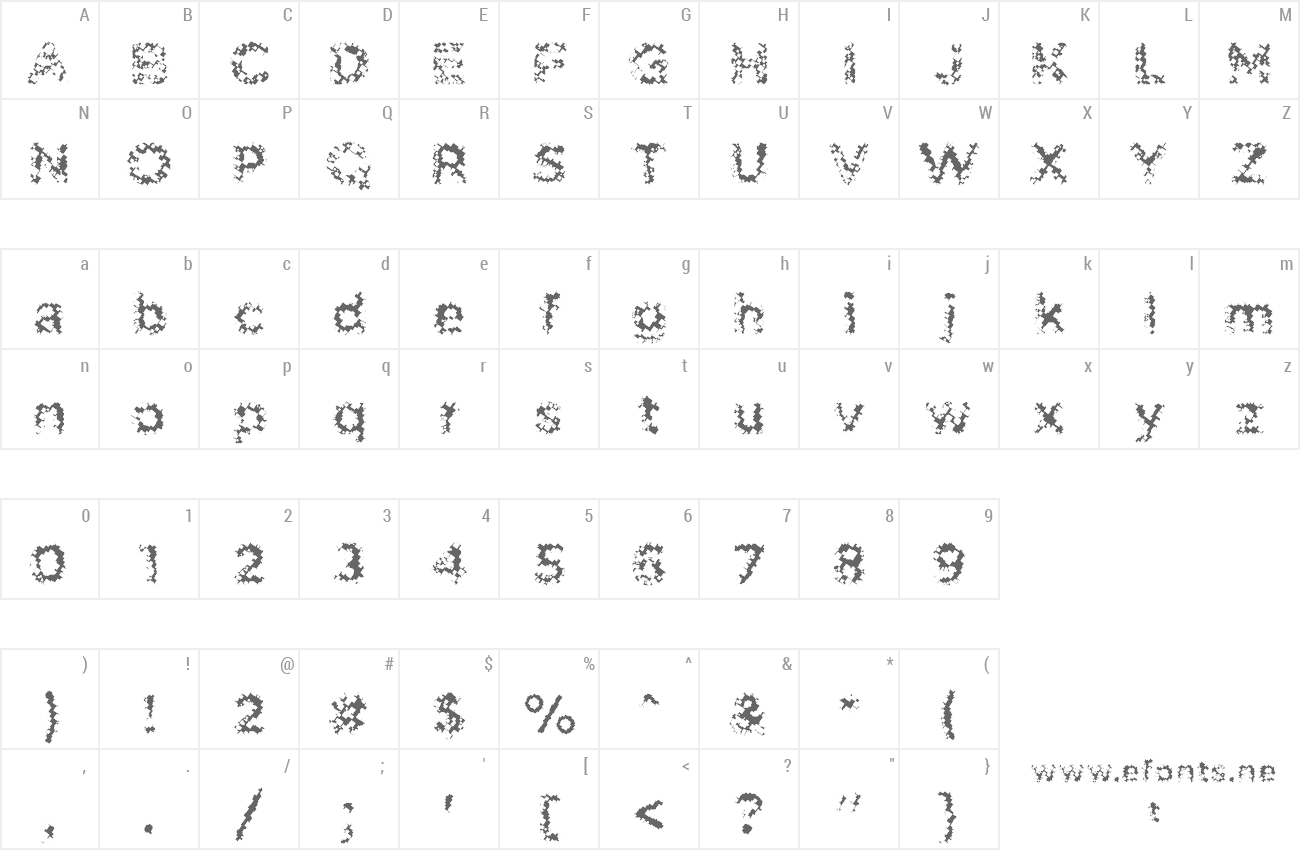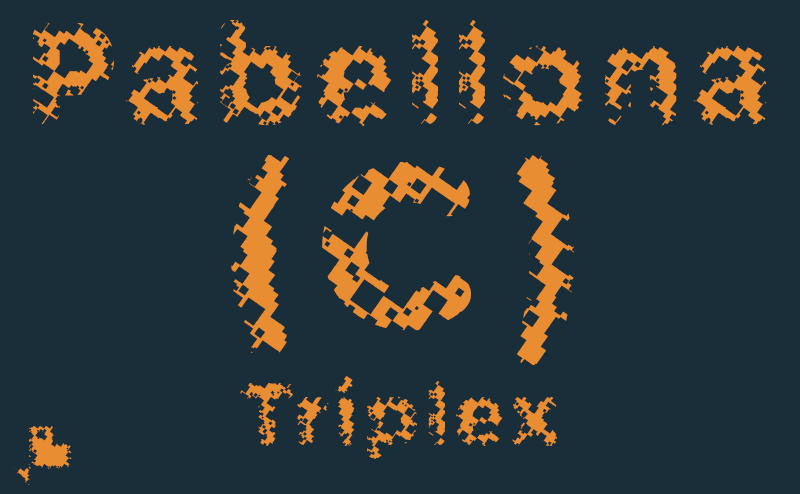
Pabellona (C) Tríplex es la tercera fuente combinable de la serie Pabellona. Crea rótulos de texto policromados con personalidad propia. Licencia comercial disponible/Available commercial license: http://defharo.com/fonts/pabellona-grunge-fonts/ |